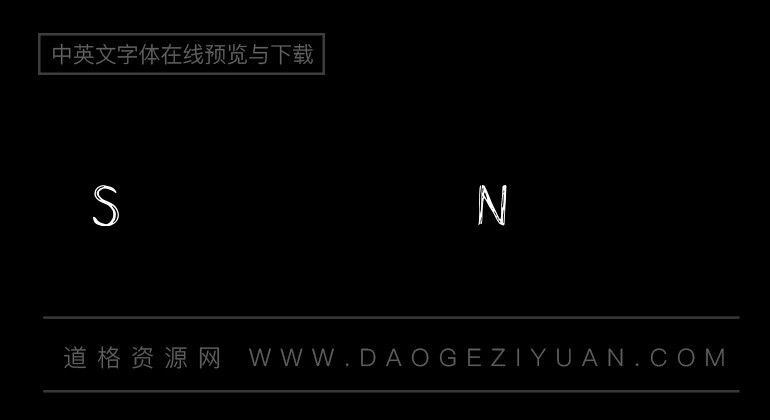
Scrawny Norah 是一种手写风格的字体,它的特点是线条细且凌乱,仿佛是由一只手轻轻涂抹而成。它的字母间距较宽,字母形状不规则,使得整个字体看起来更加自然、随意和个性化。 此字体的作者是来自英国的 James Lafuente,他在设计 Scrawny Norah 时受到了日本漫画的影响。这种字体适合用于海报、书籍封面、标语和卡片等设计中,可以营造出轻松、随意和有趣的氛围,具有很强的视觉吸引力。内容介绍
Scrawny Norah是一款非常不错的手写艺术字体,具有很好的视觉感,适合于文化类的宣传设计、商业类品牌的广告和产品包装设计以及个性化文字排版等较多场景。